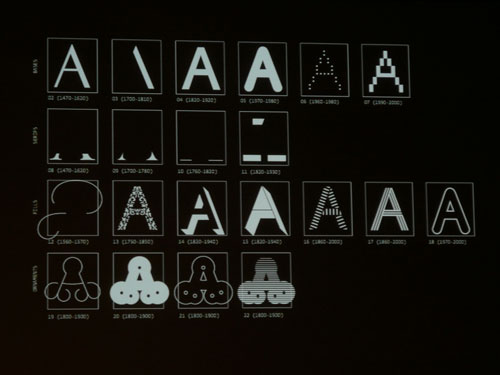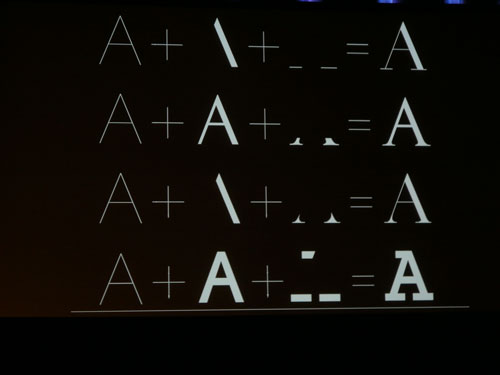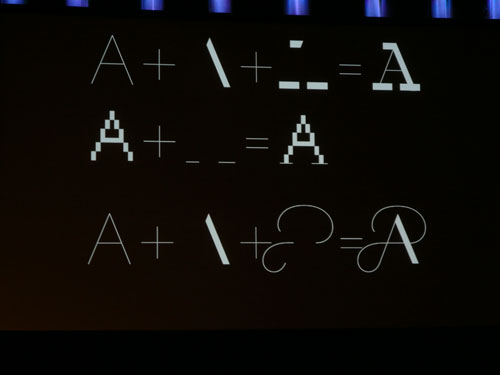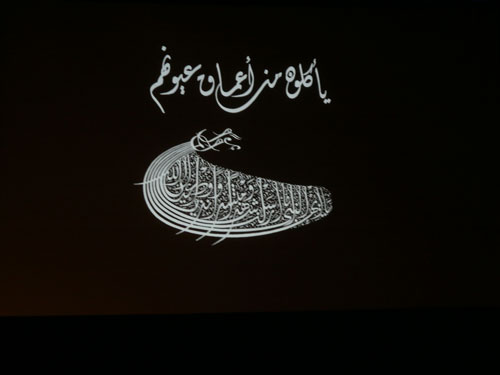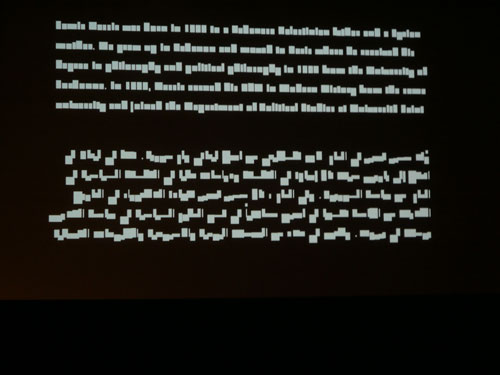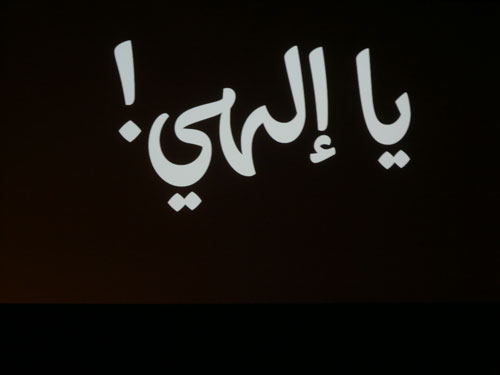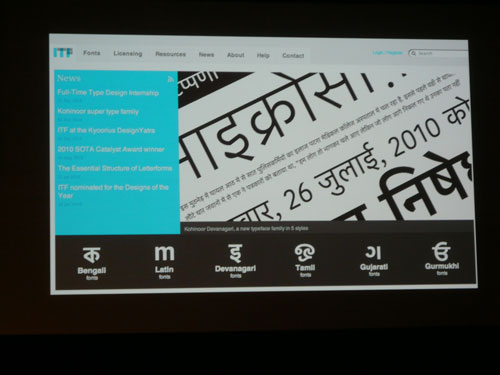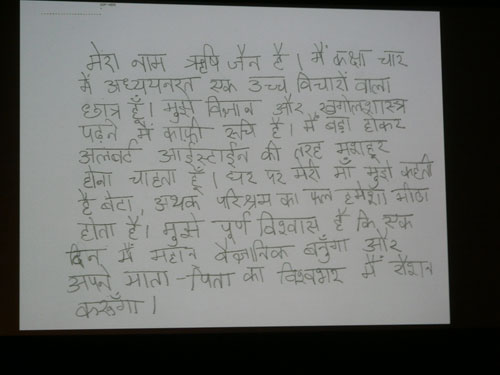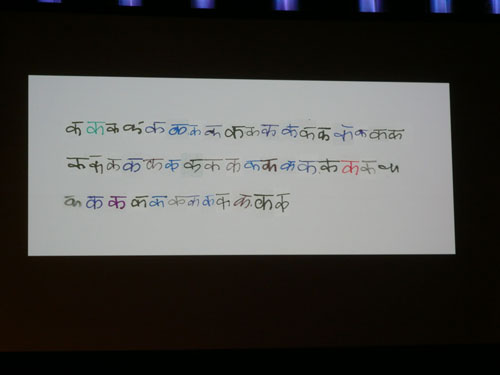
Peter Bil’ak: Mehr Typografie!
Peter Biľak ist Grafiker und Schriftgestalter, kommt aus der Slowakei und lebt im holländischen Den Haag. Für FontShop International gestaltete er mehrere Schriften und gründete schließlich seine eigene Foundry, Typotheque. Außerdem ist er Mitgründer des dot dot dot magazine und der Indian Type Foundry. 2003 entwarf Bil’ak eine Briefmarkenkollektion für die Königliche Post der Niederlande, die in einer Gesamtauflage von über 140 Millionen Exemplaren gedruckt wurde.
Biľak lehrt Typografie im Postgraduiertenstudiengang Type & Media der Königlichen Kunstakademie KABK in Den Haag und hält Vorträge zum Thema Graphic Design und Schriftgestaltung – wie hier auf der Typo Berlin. Heute ging es um Sprache, Modern Dance, Rhythmus und (natürlich) Schrift.
Unter dem Motto "Brauchen wir mehr Schriften?" ging Peter Bi`lak auf zwei große Themenkomplexe seiner Arbeit ein: Indische Schriften und Getanzte Buchstaben. Zuerst schlüsselte er die vielen Möglichkeiten zur Variation und Kombination beim Schriftenentwerfen auf. Dieses Vorgeplänkel wurde dann plötzlich weggewischt, fast als wäre das lateinische Alphabet nicht interessant genug, widmet sich Bi`lak nun der indischen Sprache. Ein unglaublich weites Feld, ohne festgelegte Standards, mit Unmengen an Sprachen, Formen, einer hohen Komplexität und reichen Kultur. Das Ziel ist, bedrohte Sprachen zu digitalisieren, damit nutzbar zu machen und zu bewahren. Zuerst muss man die Sprache verstehen, dabei arbeitet Bi`lak natürlich mit Indern zusammen. Es werden Handschriften gesammelt, verglichen, Formen definiert. Und dann digitalisiert. Ein hochkomplexer Prozess.
Während es bei den indischen Schriften um ein edles Ziel geht, ist die zweite Gruppe von Projekten extrem ästhetisch. Peter Bi`lak arbeitet mit Tänzern und Choreographen zusammen, er entwickelt Bühnenkonzepte unter anderem mit dem Nederlands Dans Theater. Er sagt, im Prinzip ist das Arbeiten für die Bühne wie das Arbeiten im Designbüro: Es geht um den Inhalt, das Konzept, das Finden des richtigen Formats um eine Botschaft zu übermitteln. Nun folgen wunderbare Beispiele. Oft sind Video und Tänzer keine Einheit auf der Bühne, sagt er, in seinem Stück visualisiert Bi`lak die Aktivität der Tänzer. Je nach Atmung, Herzrhythmus und Bewegung ändert sich die farbige Projektion, die den Tänzer umgibt. Oder ein anderes Stück. Hier wurde für ein Bühnenbild ein Raster entwickelt, nach dem Lichtröhren angeordnet werden. Bi`lak hat natürlich auch gleich ein Lichtröhren-Alphabet gemacht. Oder eine andere Arbeit sind ein Regular- und ein Bold-Schnitt eines Körper-Alphabets. Die Arbeit mit dem Körper fasziniert ihn. Der Tänzer tanzt Buchstaben, die individuell vorgegeben werden können (das gibt es auch als App! Es heißt Dance Writer.) Oder der Tänzer spielt mit seinem Schatten, auch hier entstehen Formen und Buchstaben. Ein letztes Beispiel: Ein Tänzer stellt sich in die belebte Fußgängerzone Den Haags und bewegt sich so langsam, dass die Menschen nicht erkennen können was er macht. Die ganze Zeit ist eine Kamera auf ihn gerichtet und spielt man nun den Film in 20-facher Geschwindigkeit ab, formt der Tänzer Buchstaben mit seinem Körper, während Menschenmassen an ihm vorbeirauschen. Surreal und unglaublich schön anzuschauen.
In Bi`laks Worten: The form you doing it is part of the message, not only the letters.